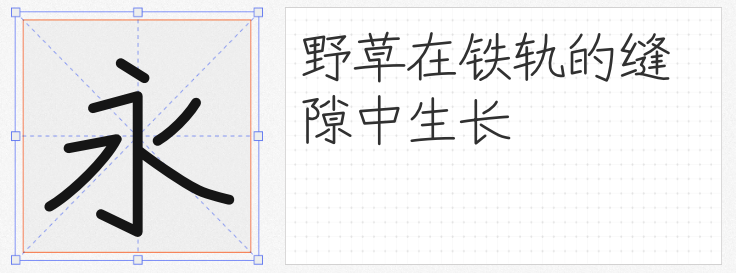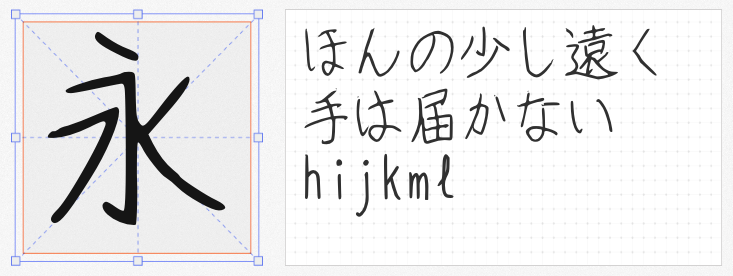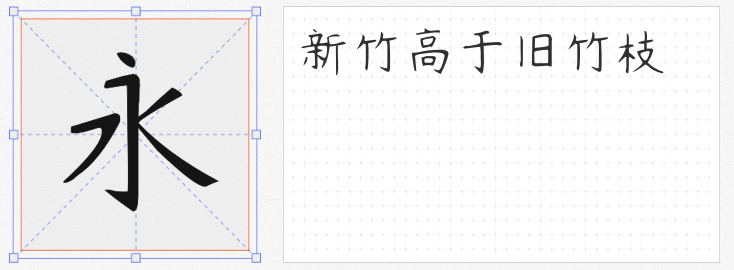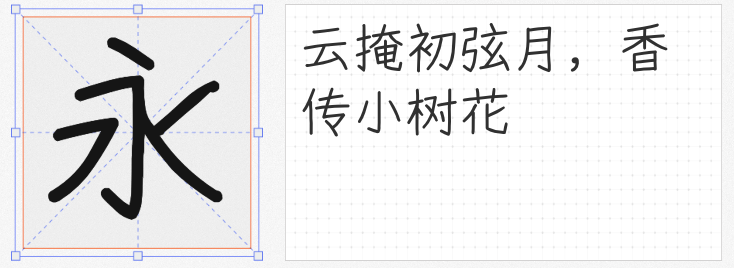
在数字化设计浪潮中,手写字体以其独特的温度感和人文气息成为品牌视觉传达的利器。本文精选四款可免费商用的优质手写字体,从创作背景到应用场景进行深度解析,助力设计师打造兼具艺术性与实用性的作品。
这款字体由设计师在笔记本上逐字书写后扫描数字化,保留了纸张纹理与墨迹渗透的原始质感。每个字符的起笔收锋都带有自然抖动,如"悠"字末笔的飞白效果,完美复现了真实书写状态。其字符集覆盖GB2312标准,特别适合用于文化类海报、手账APP等需要还原纸质触感的场景。
基于Y.OzFont改造的悠哉字体,通过部件拼接技术实现8105个通用规范汉字的全覆盖。其0.8mm纤细笔触与7°倾斜角度,营造出钢笔书写的轻盈韵律。在某茶饮品牌的包装设计中,设计师采用Medium字重搭配竖排布局,使"悠然见南山"的文案呈现出古籍装帧的雅致感。
这款由字体社区共创的字体,通过分析2000组中性笔书写样本,提炼出具有普适性的笔画特征。其独特的"断笔连意"设计,如"体"字单人旁的悬针竖,既保留书写节奏又确保屏幕显示清晰度。
作为首款支持GB2312-80标准的开源手写体,竹石体通过7档字重系统满足多元需求。以印刷体的规范,呈现手写体的精致与细腻。字母排列井然有序,造就韵律独特的篇章。
这些承载着书写者温度的数字字体,正在重新定义人机交互的情感维度。从茶饮包装到科技产品,从古籍排版到儿童教育,设计师可通过灵活运用这些资源,让每个字符都成为传递品牌价值的触点。